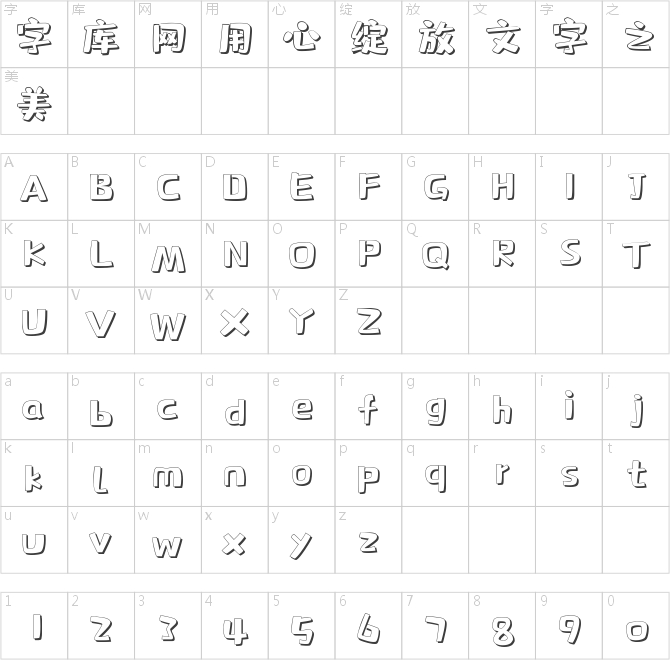
字魂39号-肥宅快乐体
该版本为空心效果字体,字符字数含6765字(包含英文、数字符号及中文简体),适用于电商标题字体的应用。
字魂39号-肥宅快乐体字体字库是一款让人赏心悦目、百看不厌的中文字体,适合各类广告和产品包装设计应用,字体大小7.79MB,格式为ttf字体,上传用户是82年的拉菲,作者/版权方为字魂